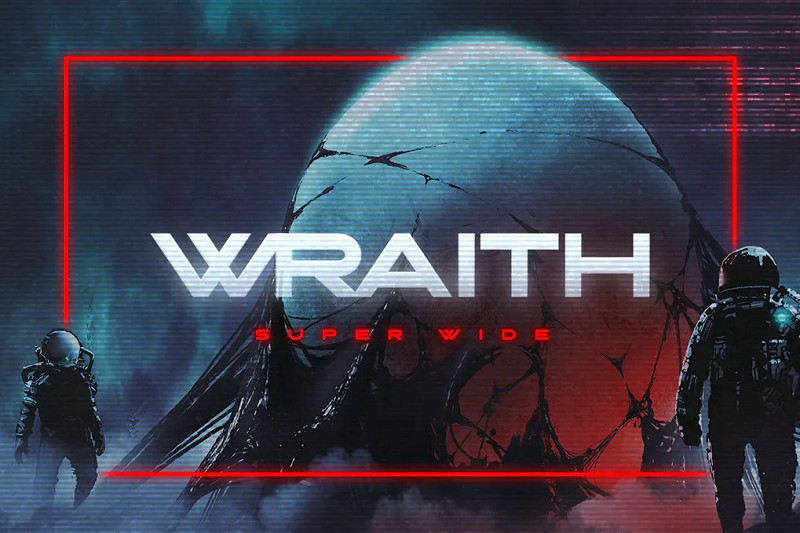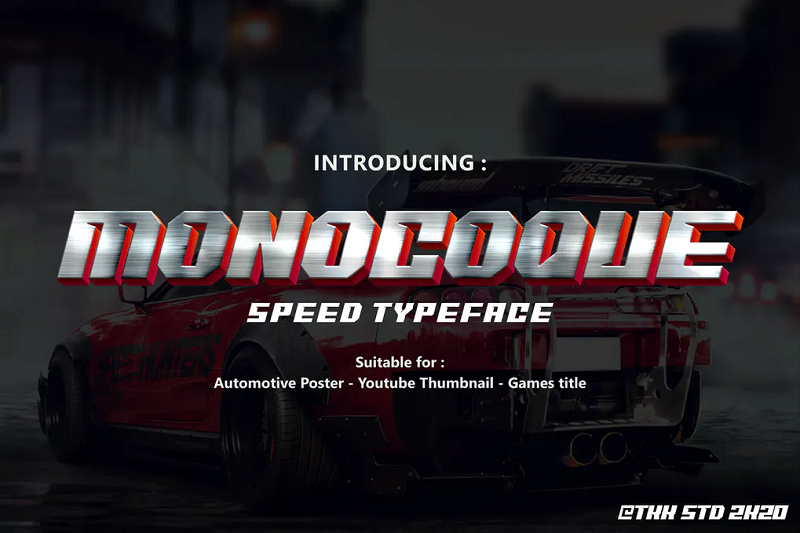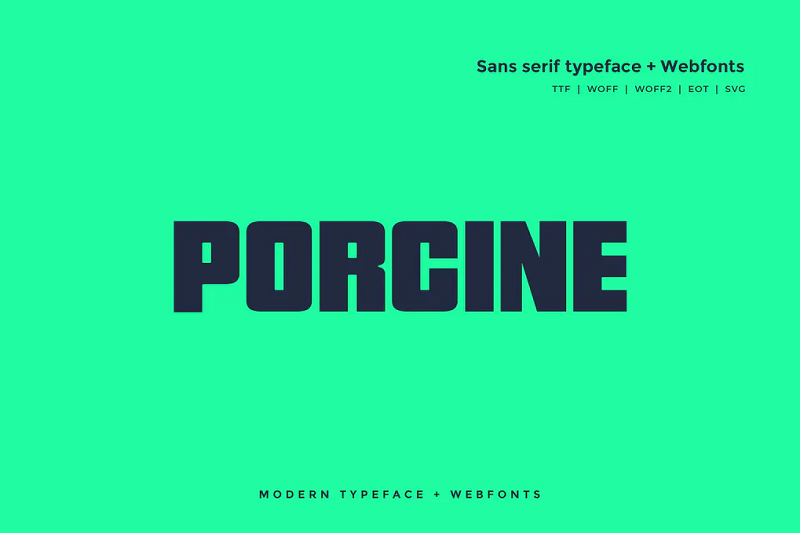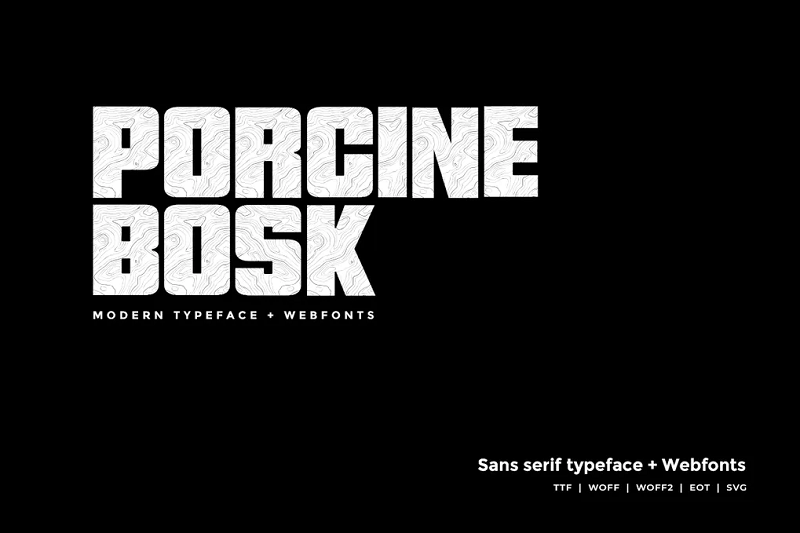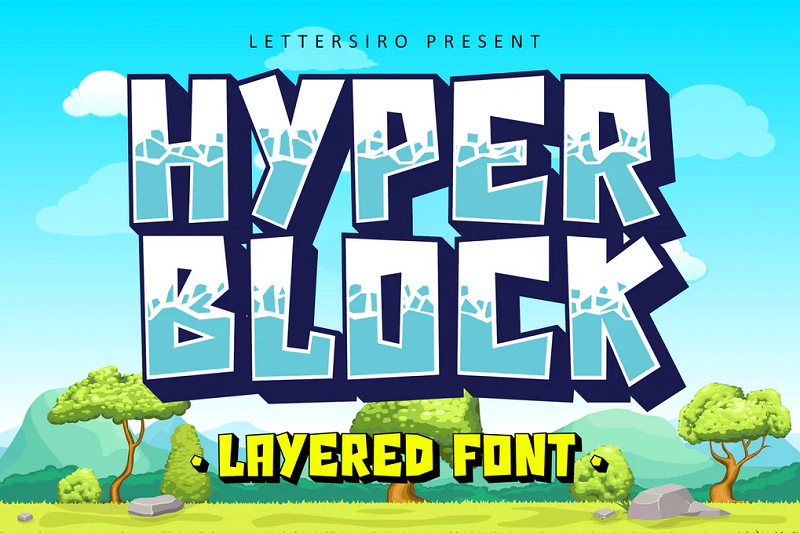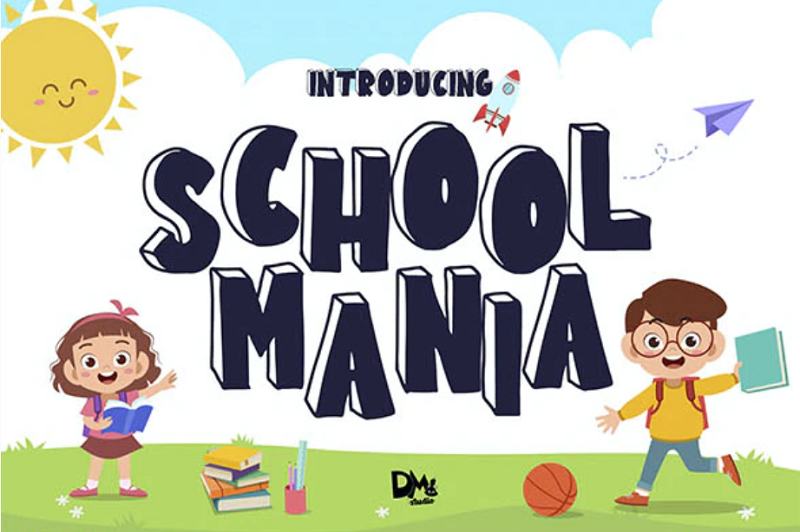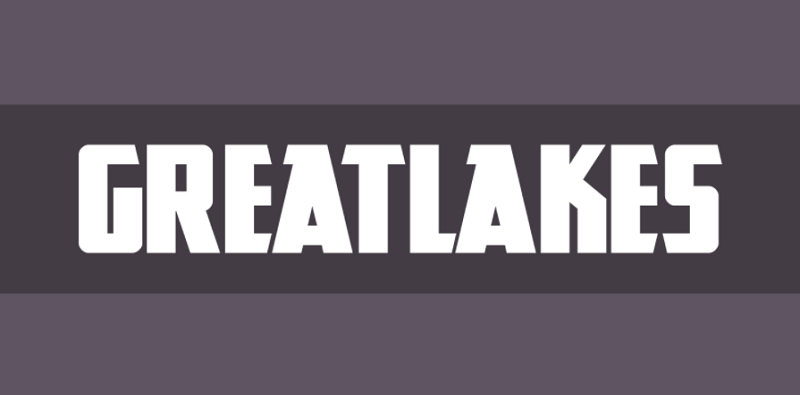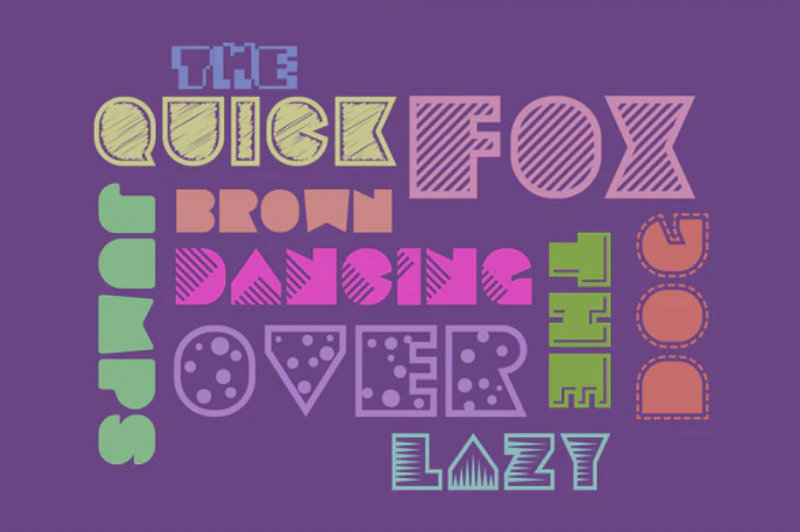
49 บล็อกฟอนต์ที่ดีที่สุดสำหรับปี 2023 (ฟรีและพรีเมียม)
เผยแพร่แล้ว: 2023-01-04เมื่อพูดถึงการดึงดูดความสนใจของผู้ชม ไม่มีอะไรจะดีไปกว่าบล็อกฟอนต์ ฟอนต์ที่ทรงพลังและดึงดูดความสนใจเหล่านี้เป็นสิ่งที่มองข้ามไม่ได้ ซึ่งทำให้เป็นตัวเลือกที่สมบูรณ์แบบสำหรับพาดหัวข่าว ป้าย โปสเตอร์ และสำเนาอื่นๆ ที่คุณต้องการให้โดดเด่น
แต่ด้วยบล็อกฟอนต์ที่แตกต่างกันมากมายให้เลือกใช้ อาจเป็นเรื่องยากที่จะหาคู่ที่เหมาะกับแบรนด์ของคุณ เพื่อช่วยคุณเปรียบเทียบตัวเลือกของคุณ เราได้รวบรวมรายชื่อบล็อกฟอนต์ที่ดีที่สุดในปี 2021
เราได้รวมตัวเลือกทั้งแบบฟรีและแบบพรีเมียมไว้ด้วยกัน ดังนั้นควรมีบางอย่างที่นี่เพื่อให้เหมาะกับทุกงบประมาณ
บล็อกฟอนต์คืออะไร?
ฟอนต์แบบบล็อกเป็นฟอนต์ประเภทกว้างๆ ที่อ่านง่าย และใช้บ่อยที่สุดในป้ายโฆษณา พาดหัวข่าว และการออกแบบกราฟิกอื่นๆ ที่จำเป็นต้องใช้ฟอนต์ขนาดใหญ่
พวกเขามักจะมีลักษณะสำคัญบางประการร่วมกัน ได้แก่ :
- ตัวพิมพ์ใหญ่ทั้งหมด
- ความหนาของเส้นขีดสม่ำเสมอ (แม้ว่าบล็อกฟอนต์ที่มีศิลปะมากกว่าบางตัวจะมีโซนที่บางและหนากว่าสำหรับอักขระที่เพิ่มเข้ามา)
- มุมฉากและเส้นตรง
- แบบอักษร Slab serif (ยกกำลังสองปิด serif)
แบบอักษรบล็อกที่ดีที่สุด 49 อันดับแรก (2023)
เอาล่ะ ข้ามไปที่รายการกันเลย ต่อไปนี้คือบล็อกฟอนต์ยอดนิยม 49 อันดับของเราในปี 2023
1. ฟอนต์เกม Black Block
เรามาเริ่มกันที่บล็อกฟอนต์ตัวหนาและขี้เล่นจาก Envato Elements ตัวอักษรหนาและขอบโค้งมนทำให้แบบอักษรนี้ดูสนุกและเป็นมิตรกับเด็ก ใช้งานได้ดีกับเกมสำหรับเด็ก หน้าปกช่องเกมบน YouTube ของเล่นเด็ก สินค้า และโปสเตอร์
2. กระแสน้ำ
The Tide เป็นฟอนต์ที่สื่อถึงแสงแดด ทะเล และคลื่น บล็อกฟอนต์ที่ได้รับแรงบันดาลใจจากการผจญภัยบนชายหาดนี้ใช้การออกแบบที่ไร้กังวลซึ่งจะดูดีบนหน้าปกช่องการท่องเที่ยวของ YouTube ร้านขายอุปกรณ์โต้คลื่น ชุดชายหาด นิตยสาร และอื่นๆ
เป็นแบบอักษรที่ไม่จริงจังเกินไปและอาจดูไม่เหมาะสมในสภาพแวดล้อมแบบมืออาชีพหรือในองค์กร แต่ถ้าคุณต้องการสร้างเอกลักษณ์ของแบรนด์แบบสบาย ๆ เป็นตัวเลือกที่ยอดเยี่ยม
3. ขี้เหนียว
Glubby เป็นอีกหนึ่งแบบอักษรดิสเพลย์ที่สนุกและแปลกใหม่ที่กระโดดออกจากหน้า เหมาะสำหรับสินค้าสำหรับเด็กและวัสดุของแบรนด์ เช่น ปกหนังสือสำหรับเด็ก แบรนด์เสื้อผ้าเด็ก ชื่อเรื่องการ์ตูน และโปสเตอร์ ตัวอักษรหนามากซึ่งทำให้ตัวอักษรโดดเด่นและช่วยให้อ่านง่าย
4. ต้นเอล์ม
Old Elm เป็นฟอนต์เซอริฟแผ่นพื้นขรุขระที่ใช้การออกแบบที่วาดด้วยมือที่ได้แรงบันดาลใจจากวินเทจ นักออกแบบร่างตัวละครแต่ละตัวด้วยมือด้วยดินสอก่อนที่จะแปลงเป็นฟอนต์ดิจิทัล และด้วยกระบวนการนี้ ฟอนต์จึงมีรูปลักษณ์ย้อนยุคแบบเก่า
บรรจุภัณฑ์ประกอบด้วยสี่รูปแบบในพื้นผิวและน้ำหนักที่แตกต่างกัน: ปกติ หยาบ เรียบ และประทับตรา ประกอบด้วยอักขระทุกตัวบนแป้นพิมพ์ของสหรัฐอเมริกา ตลอดจนแป้นสากลบางแป้น เช่น สัญลักษณ์ปอนด์อังกฤษและยูโร
5. เครดิตครบกำหนด
Due Credit ได้รับการออกแบบมาโดยเฉพาะเพื่อใช้ในโปสเตอร์ภาพยนตร์ ผู้ออกแบบต้องการสร้างบางสิ่งที่อ่านง่ายซึ่งยังคงมีรูปลักษณ์แบบภาพยนตร์คลาสสิกเพื่อใช้ในบล็อกเครดิต
ตามที่ตั้งใจไว้ ฟอนต์ดูมีบรรยากาศและมีกลิ่นอายของหน้าจอขนาดใหญ่มากโดยไม่ส่งผลเสียต่อความสามารถในการอ่าน มีหลายน้ำหนักและสองรุ่นที่แตกต่างกัน แพ็คเกจนี้ยังรวมถึงร่ายมนตร์นักแสดงและลูกเรือเพิ่มเติม และรูปแบบที่ได้รับแรงบันดาลใจจากแนว 'สยองขวัญ' เพิ่มเติม
6. บอลล็อค
Ballocs เป็นแบบอักษรบล็อกที่มีพื้นผิวพร้อมการออกแบบที่ดูสปอร์ตมาก สามารถอ่านได้ง่ายมากและใช้งานได้ดีในฐานะแบบอักษรที่แสดงบนโลโก้ พาดหัวข่าว สกอร์บอร์ด ตลอดจนชุดกีฬาและภาพพิมพ์กีฬาอื่นๆ
ชุดฟอนต์ประกอบด้วยตัวพิมพ์ใหญ่ ตัวพิมพ์เล็ก ตัวเลข เครื่องหมายวรรคตอน และสัญลักษณ์ และมาในรูปแบบ OTF และ TTF หากคุณกำลังทำงานเกี่ยวกับการออกแบบที่เกี่ยวข้องกับกีฬา ก็เป็นตัวเลือกที่ดี
7. บล็อกลึก
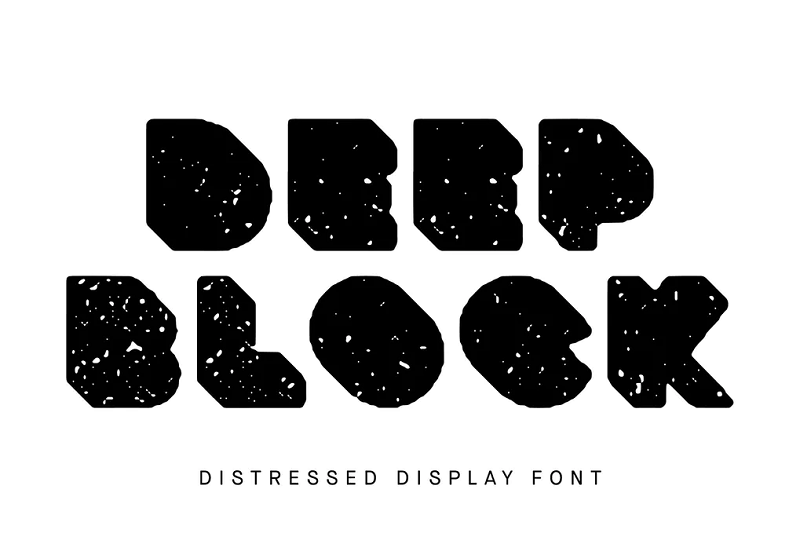
Deep Block เป็นฟอนต์บล็อกตัวหนาที่มีพื้นผิวเก่า เหมาะอย่างยิ่งเมื่อคุณกำลังมองหาลุคสุดเท่และต้องการสร้างจุดเด่นให้กับงานออกแบบของคุณ แบบอักษรที่มีปัญหาให้ความรู้สึกวินเทจและอินดัสเทรียลที่มีความทันสมัย ไม่ใช่ฟอนต์ที่อ่านง่ายที่สุดในรายการนี้ แต่เป็นหนึ่งในฟอนต์ที่น่าสนใจที่สุด
8. บล็อกทันทีทันใด
Block Glitch เป็น 'แบบอักษรเฉพาะสำหรับการออกแบบสมัยใหม่' อย่างที่คุณอาจเดาได้จากชื่อ มันเป็นบล็อกฟอนต์แห่งอนาคตที่มีอักขระที่ดูเหมือนจะ 'ผิดพลาด' นักออกแบบได้ใช้เส้นตรงหักล้างกับจุดบกพร่องและข้อผิดพลาดโดยเจตนาที่บิดเบือนข้อความเพื่อให้ความรู้สึกล้ำยุค
แม้จะมีการออกแบบที่เหมือนความผิดพลาด แต่ก็ยังสามารถอ่านได้ง่ายและเหมาะสำหรับโครงการแสดงผลที่หลากหลาย
48. Pikolo Block Alt
ต่อไป เรามีฟอนต์ Pikolo Block Alt ฟอนต์สำหรับแสดงผลที่ไม่เหมือนใครนี้มีการออกแบบที่น่าสนใจพร้อมมุมโค้งมน อักขระถูกสร้างขึ้นจากบรรทัดที่แยกจากกันซึ่งสร้างตัวอักษรและบางครั้งก็พันกัน
49. ถนน
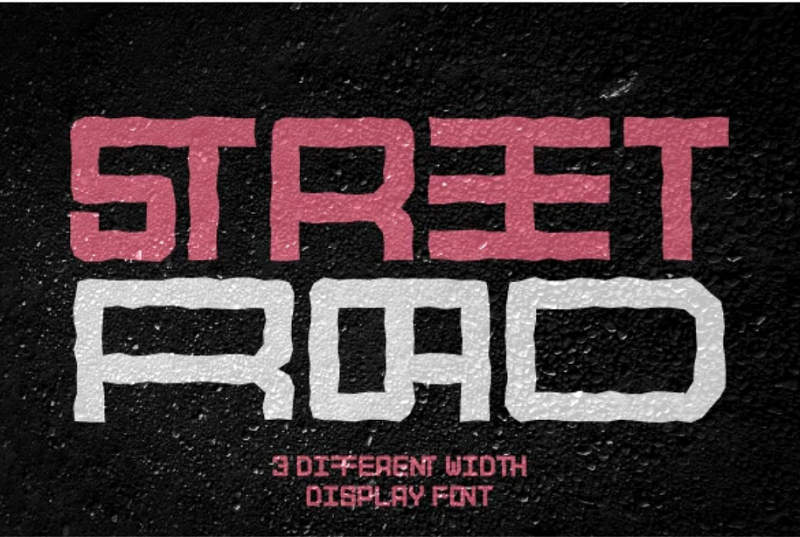
สุดท้าย แต่ไม่ท้ายสุด เรามี Street Road โดย PutraCetolStudio ฟอนต์ดิสเพลย์สไตล์เมืองสุดล้ำนี้มีให้เลือกสองสไตล์: สะอาดและหยาบ มีเส้นหยักและมีความกว้างต่างกัน 3 แบบ